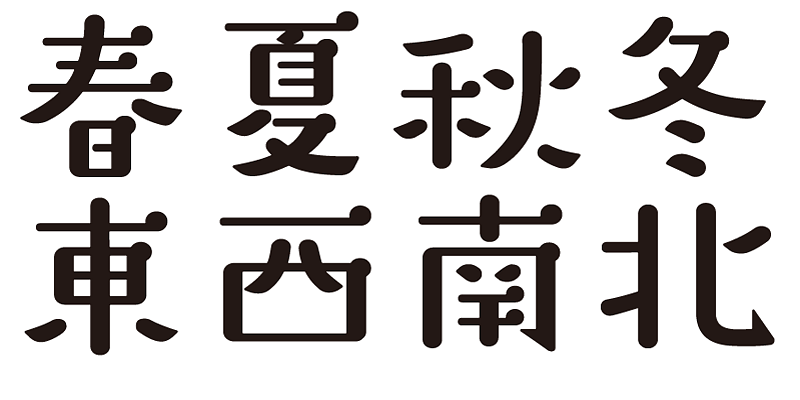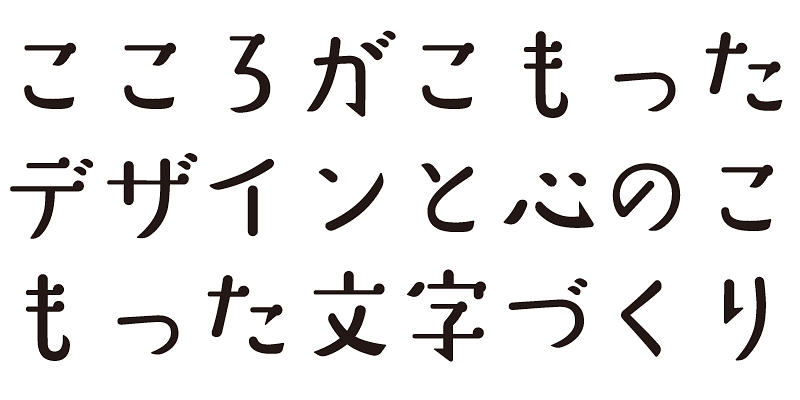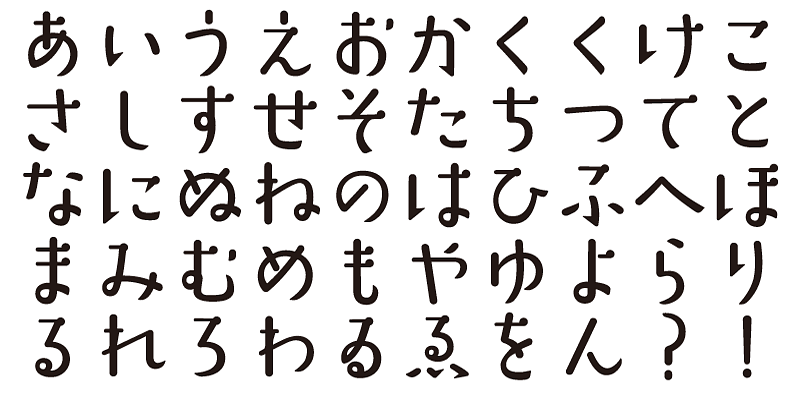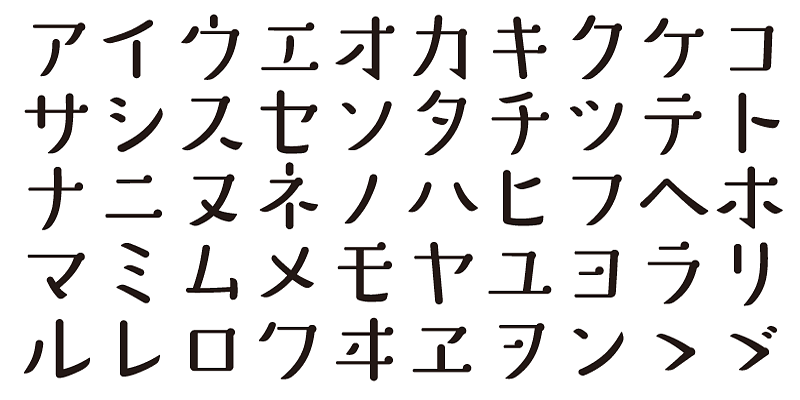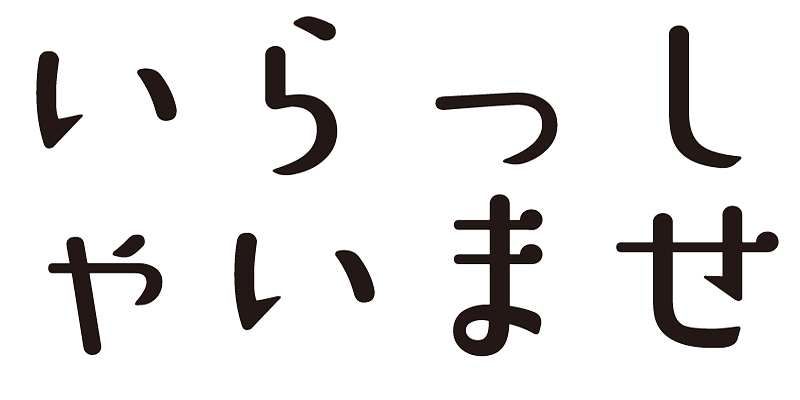
이 서체는 마음을 열게 하는 특징을 갖고 있어 편안한 분위기를 제공하고 긴장감을 해소할 수 있습니다.
이 서체의 각 글꼴에는 1,000개의 간지 문자를 비롯하여 히라가나, 카타카나, 영숫자, 구두점이 포함되어 있습니다.
우리는 표현된 단어에 기본 의미를 더하고자 하는 마음으로 서체를 디자인합니다. 이 서체를 사용하면 만족감을 느끼고 편안함과 즐거움을 동시에 누릴 수 있습니다.